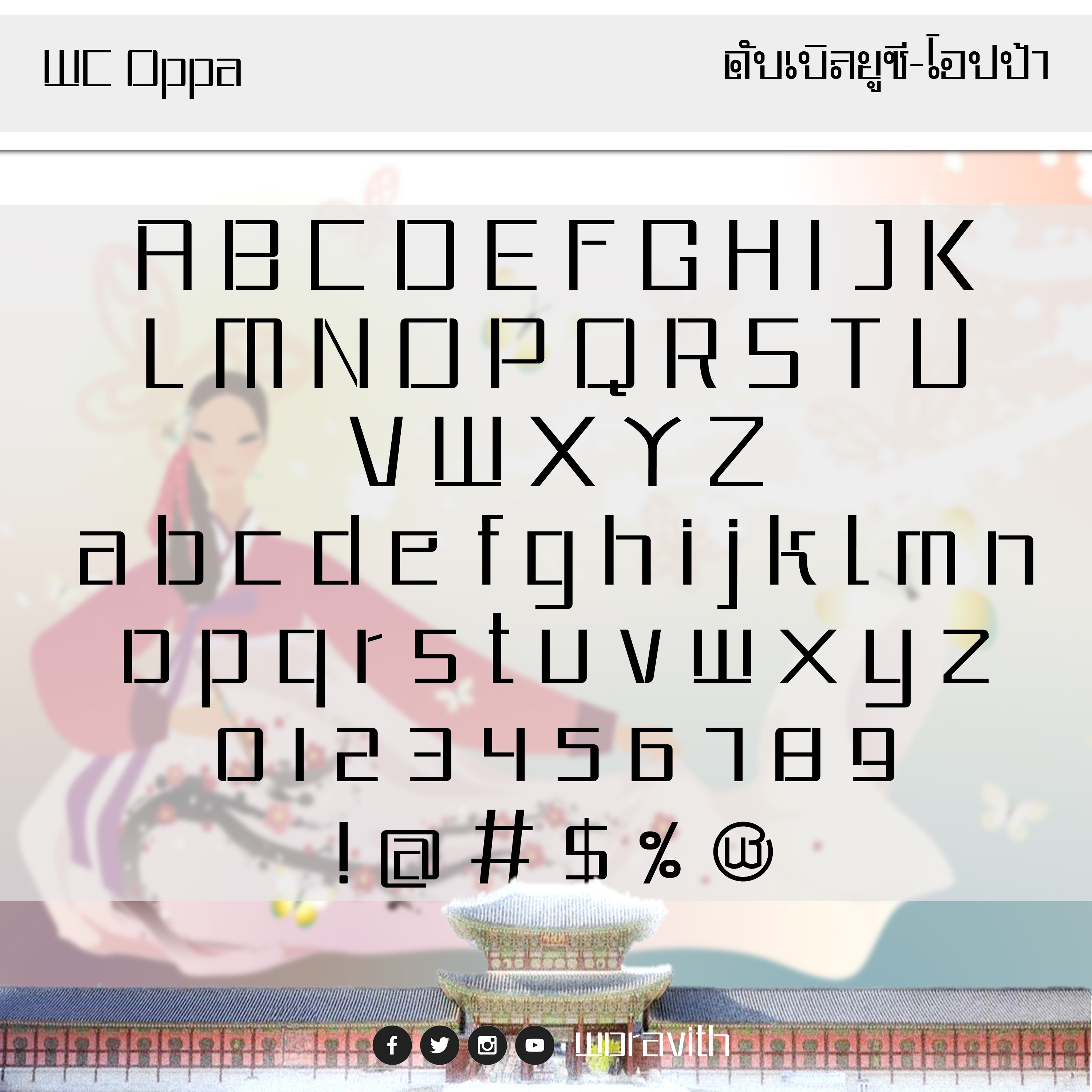
ดับเบิลยูซี โอปป้า : WC OPPA
ชื่อฟอนต์ : ดับเบิลยูซี โอปป้า
Font Name : WC OPPA
ผู้สร้างสรรค์ : วรวิทย์ จันทร์สุวรรณ
Creator : Woravith Chansuvarn
ลำดับฟอนต์ : 4
#แรงบันดาลใจจาก feed หนึ่งใน facebook
ลองเขียนร่างขึ้นมาคร่าวๆ ว่าพอที่ทำตัวอื่นได้ไหม ร่างไป แก้ไป ประมาณนี้...
เริ่มทำตัวแรก คือ ย หน้าตาออกมาแบบนี้เลย
ผมกลับมองว่าถ้าปรับตัวกลมเป็นวงรีตั้งทั้งหมดอาจจะสวยกว่า แล้วแก้ปัญหาความสูงด้วยการขยายขึ้นไปข้างบนน่าจะโอเคครับ แต่ขนาดนี้ก็ชื่นชมในความขยันแล้วครับ โปรเจกใหม่ออกมารัว ๆ เลยครับ
ฟอนต์ไทยสไตล์เกาหลีนี่มีโอกาสได้ใช้บ่อยมากๆ แน่นอน
ชื่อฟอนต์ : ดับเบิลยูซี โอปป้า
Font Name : WC OPPA
ผู้สร้างสรรค์ : วรวิทย์ จันทร์สุวรรณ
Creator : Woravith Chansuvarn
#แรงบันดาลใจจาก feed หนึ่งใน facebook